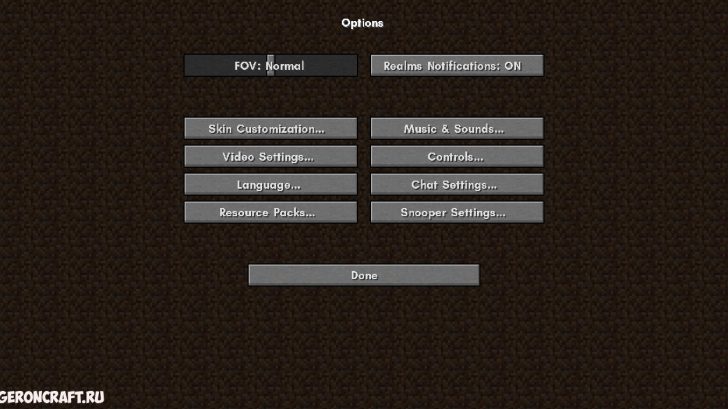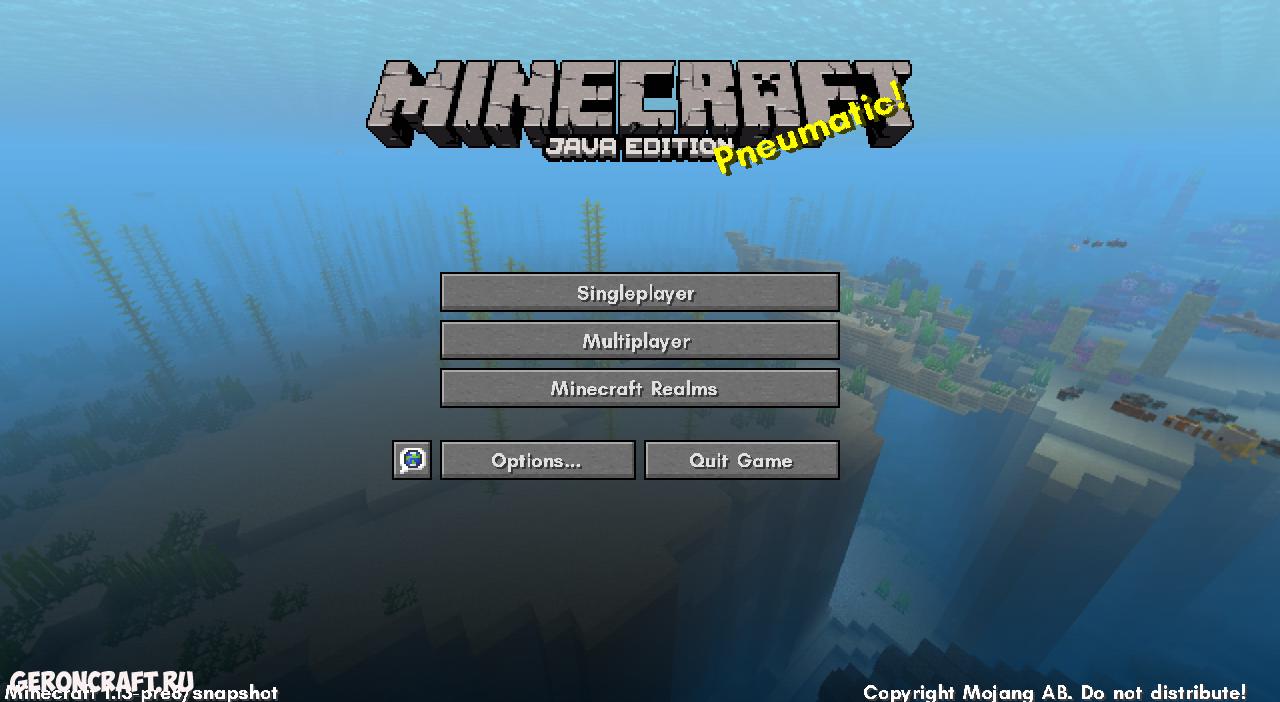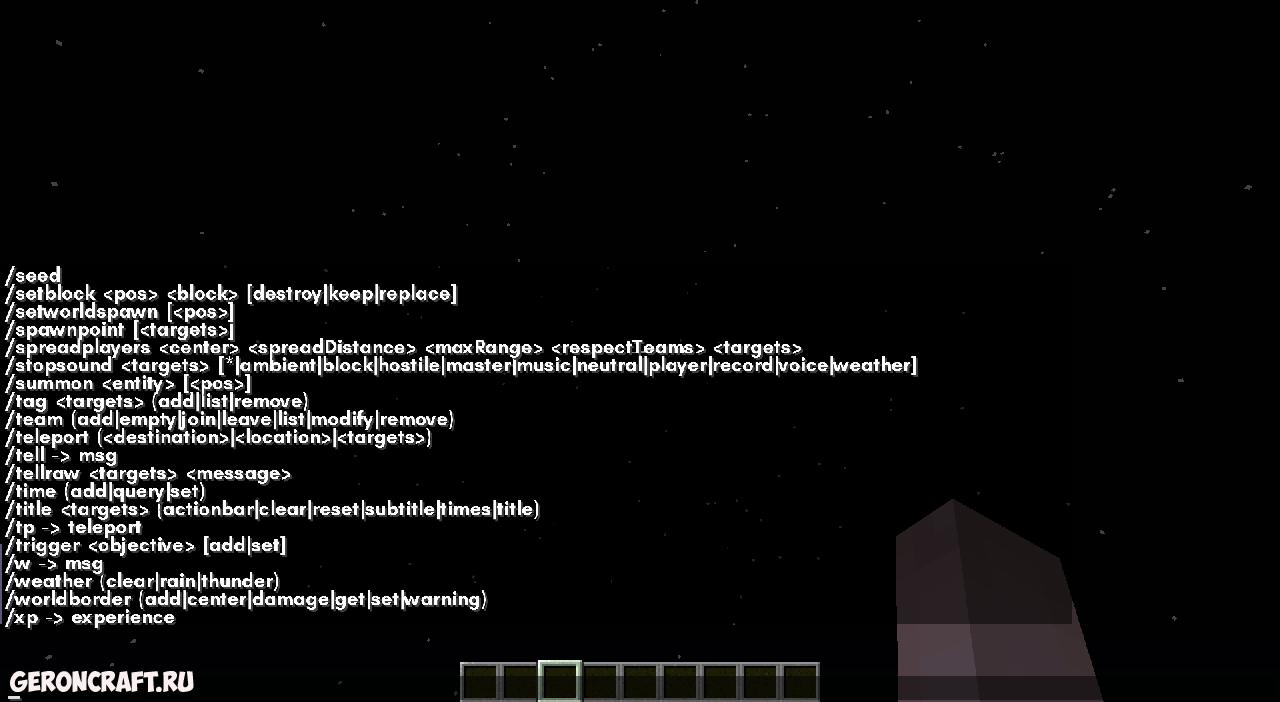
Открытый шрифт, который похож на Google’s.
Этот пакет ресурсов изменяет ваш шрифт Minecraft на более качественный во всех меню. Он совместим с меньшим количеством языков, чем шрифт по умолчанию, знайте об этом, когда вы можете увидеть некоторые пиксельные буквы. Вы можете использовать это вместе с любым другим пакетом ресурсов, просто переместите его наверх в порядке активированных пакетов ресурсов.
Glacial Indifference — это шрифт без засечек с открытым исходным кодом, разработанный Hanken Design Co.
автор выбрал этот шрифт, потому что он выглядел лучше похож на известный продукт Google Sans от Google, который используется в интерфейсе Android Pie и отлично смотрится на Minecraft! Единственная проблема — отсутствие специальных букв с акцентом, но это не должно влиять на большинство пользователей.